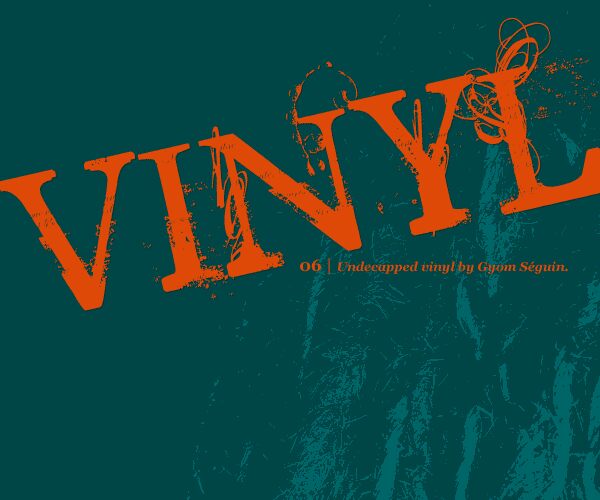
Undecapped Vinyl von Gyomsegs ist eine kostenlose Display-Schrift mit abgenutztem Druck-Look, durchzogen von vinylartigen Schnörkeln in den Buchstaben. Die Großbuchstaben erinnern an alte Serifenschriften, die abgekratzt, überdruckt und mit dekorativen Ornamenten versehen wurden – so wirkt die Schrift wie eine Mischung aus verwitterten Plakaten und analogem Grafik-Chaos.
Sie passt perfekt zu Musik-Flyern, Platten-Covern, Bar-Postern, Titelkarten und Überschriften, bei denen die distressed Oberfläche einen Teil der Geschichte erzählt. Als kostenlose Schrift eignet sie sich zudem hervorragend für schnelle Monogramme oder kurze Branding-Elemente. Halten Sie sich kurz – dank der detailreichen Textur und den geschwungenen Akzenten wirken selbst wenige Buchstaben ausdrucksstark genug.